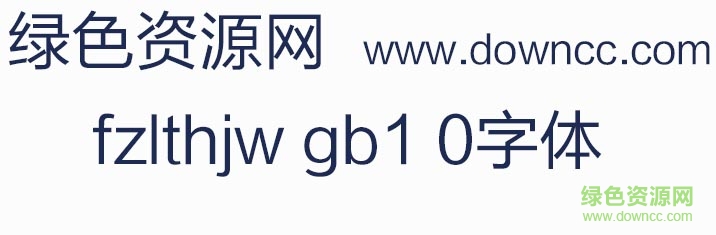
fzlthjw gb1 0字体为方正字库自主精心设计开发的黑体字体,不管是常用字或是非常用字,字字精美、结构端正、重心平稳、美观实用,适用于标题、小标题、正文、屏显等。欢迎下载。
fzlthjw gb1 0是比较常用的方正简体字体,此款简洁大气,字体线条偏粗,具有引人注目的特点,常用于标题制作、名片设计、封面排版等领域,需要的朋友欢迎来下载!